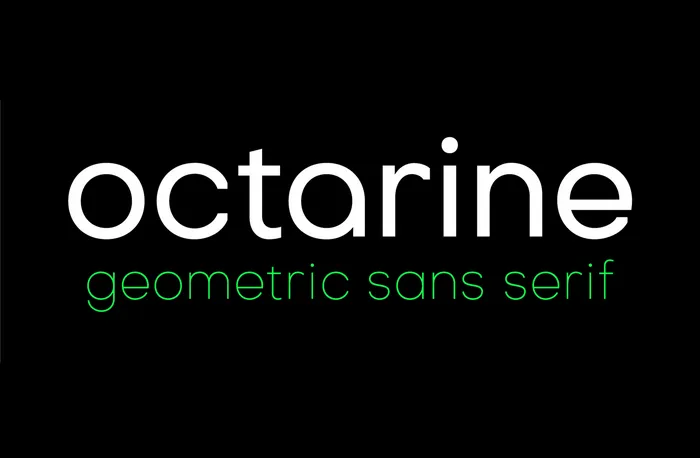
Descubra Octarine Font Family, uma famosa família de tipo geometrica sans serif apresentada por Alexander Slobzheninov. Baseado na arquitetura do Bauhaus clássica, Octarine é perfeito para criar logotipos modernos e contemporâneos, como parafeitos cartazes ou capas de livros. Através de sua composição geométrica baseada em grids, Octarine oferece um equilíbrio entre formas suaves e linhas aguçadas que conferem uma aparência amigável e forte a seus elementos tipo. Ideal tanto para títulos quanto para textos detalhados, Octarine é uma fonte universal que se destaca como uma opção confiável para qualquer projeto de design, seja ele digital ou impresso. Se você já usa Octarine, compartilhe sua experiência; se ainda não tem a chance, esta oferta gratuita é uma ótima oportunidade para adicionar-a à coleção de fontes em seu dispositivo.